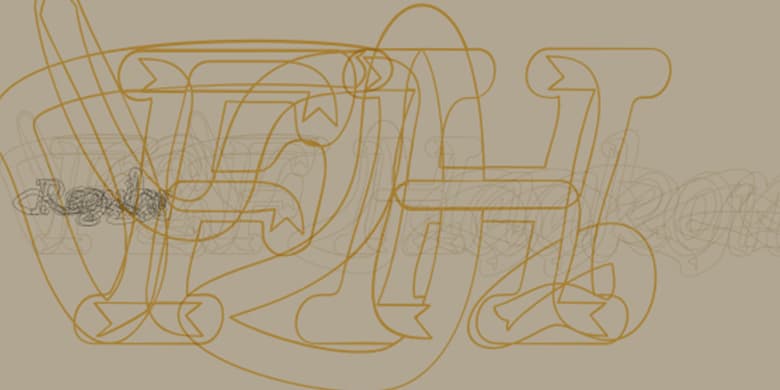
品牌:Linotype(Monotype)设计师:Stefan,Hauser发行时间:2020字库编码:Unicode分类:字体属性:
20世纪90年代中期的Techno sound,个人电脑以及新的字体创作软件都成为F2F(Face2Face)字体家族的灵感来源。Stefan Hauser和他的朋友们需要创作新颖的不同寻常的字体,这些字体应该在德国领先的技术杂志《 Frontpage》中使用。即使是排版时大小最小设置为6pt,布局也几乎无法辨认,孩子们还是能很愉悦地阅读并解读这些信息。
F2F Haakonsen是Linotype GmbH的Take Type 5家族中包含的41种Face2Face字体之一。Hauser自己设计了其中两个。”
The Face2Face (F2F) series was inspired by the techno sound of the mid-1990s, personal computers and new font creation software. For years, Stefan Hauser and his friends formed a unique type design collective, which churned out a substantial amount of fresh, new fonts, none of which complied with the traditional rules of typography. Many of these typefaces were used to create layouts for the leading German techno magazine of the 1990s, Frontpage. Hauser and his fellows would even set in type at 6 points, in order to make it nearly unreadable. It was a pleasure for the kids to read and decrypt these messages!
F2F Haakonsen is one of 41 Face2Face fonts included in the Take Type 5 collection from Linotype GmbH. Hauser designed two of these himself."